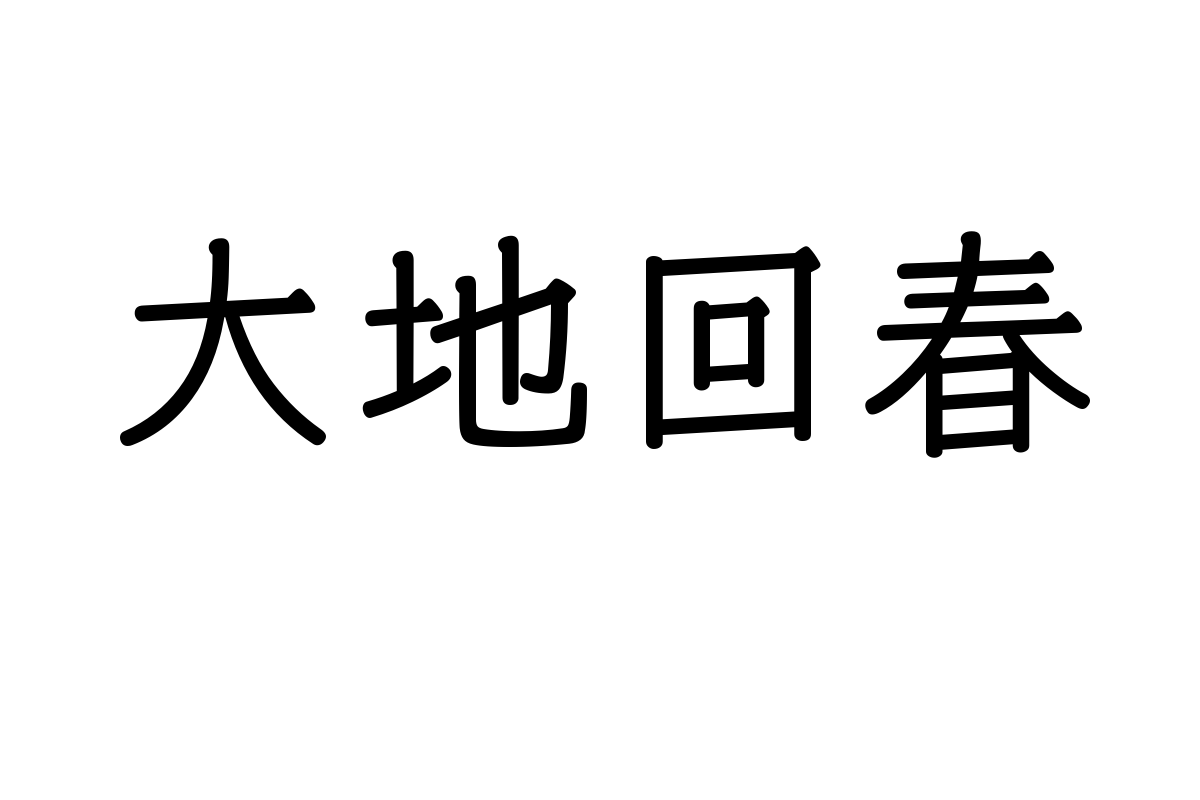
“也字工厂淡淡黑”是一套字体,由”也字工厂”设计团队开发。这款字体以其简洁、现代的设计而闻名,适合用于各种商业和品牌推广的场合。
特点:
– 清晰易读:该字体具有清晰的字形和合理的字间距,确保文字在各种尺寸和距离下都能清晰阅读。
– 现代感:采用现代设计元素,如简洁的线条和干净的轮廓,使整体看起来更加时尚和现代。
– 可定制性:虽然是一款免费字体,但”也字工厂”提供了多种不同的字重和样式选择,用户可以根据自己的需求进行个性化定制。
– 多用途:适用于各种应用场景,包括网页设计、平面设计、广告宣传等。
总之,”也字工厂淡淡黑”是一款实用且美观的字体,适合需要清晰、易读、现代风格的设计师使用。